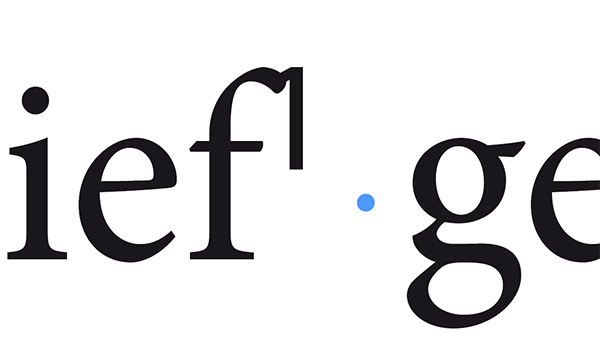
Fußnotenverweise: Kollision mit Buchstaben
ich arbeite gerade an der Vorlage zu einer Facharbeit und habe in Indesign das Problem, dass sich die hochgestellten Fußnotenverweise im Fließtext manchmal mit den Buchstaben überlagern und unschöne Gebilde entstehen (Schrift ist Minion). Gibt es einen Weg, im dazugehörigen Zeichenformat einen generellen Abstand einzustellen oder so ähnlich? Eigentlich sollte das optische Kerning solche Kollisionen doch vermeiden, oder?
Hier das Beispiel:
Getestet mit der Minion Pro (falls es einen unterschied macht): Wenn du statt der "normalen" (also mathematisch skalierten, falschen) Hochstellung die bessere Opentype-Hochstellung als Formatierung verwendest, kollidieren f und die hochgestellte 1 nicht mehr. Sie stehen immer noch sehr nahe, da es kein Kerning für das Paar gibt, aber besser als die Alternative. Und die f-Kombinationen werden vermutlich die schlimmstmöglichen sein die vorkommen.
Die Formatierung für Fußnoten-Ziffern kannst du unter Schrift > Fußnotenoptionen einstellen. Dort bei Formatierung die "Zeichenlage" auf Normal stellen (nicht hochgestellt) und stattdessen dann als Zeichenformat ein eigens erstelltes Zeichenformat auswählen, das eben hochgestellte Opentype-Ziffern eingestellt hat.
Getestet mit der Minion Pro
Die hochgestellte 1 in Deinem Screenshot sieht gar nicht nach Minion aus, wird die vielleicht aus einer Ersatzschrift dargestellt?
Optisches Kerning ist eh böse,™ gerade bei Qualitätsfonts, zu denen ich die Minion zählen würde, sollte man in InDesign das Kerning auf "Metrisch" schalten.
Zumal ja in dem Fall auch nicht die Fußnote selbst falsch sitzt, sondern das f einfach so eine starke negative Nachbreite hat. Und ein Kerning-Paar dürfte auch nicht greifen, da für InDesign da ja nur ein variables Steuerzeichen und keine konkrete Glyphe steht. Im Zweifel würde ich f-Fußnoten-Kombinationen einfach am Ende der Satzarbeit suchen und manuell eingreifen. Ich wüsste nicht, bei welchen anderen Buchstaben das Problem noch auftreten würde.
Die hochgestellte 1 in Deinem Screenshot sieht gar nicht nach Minion aus, wird die vielleicht aus einer Ersatzschrift dargestellt?
Das war Myriad, habe ich aber jetzt geändert. Die Fußnoten sind aber momentan noch in Myriad gesetzt. Ist alles noch nicht entgültig...
Hier nochmal der Fußnotenverweis: